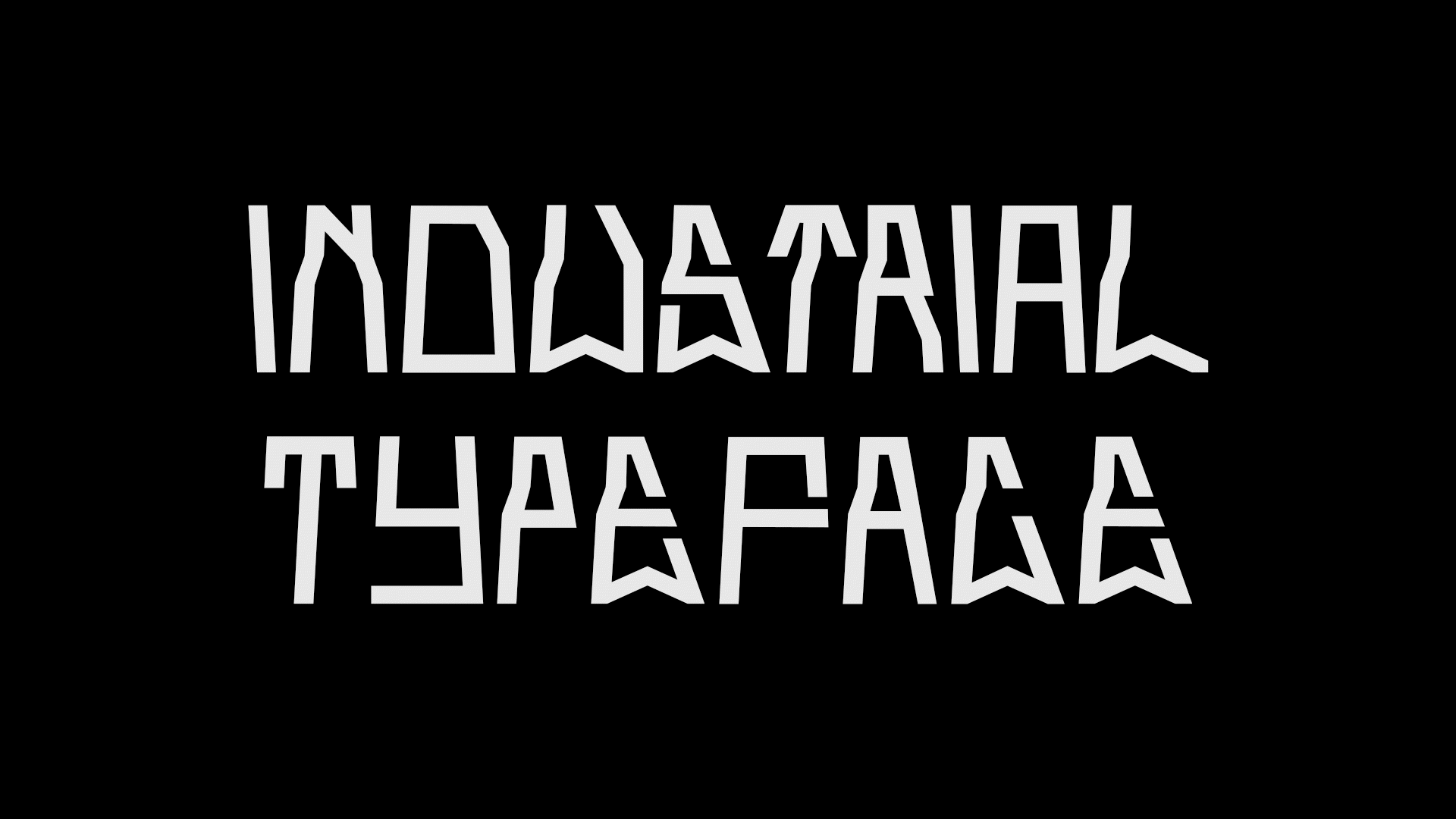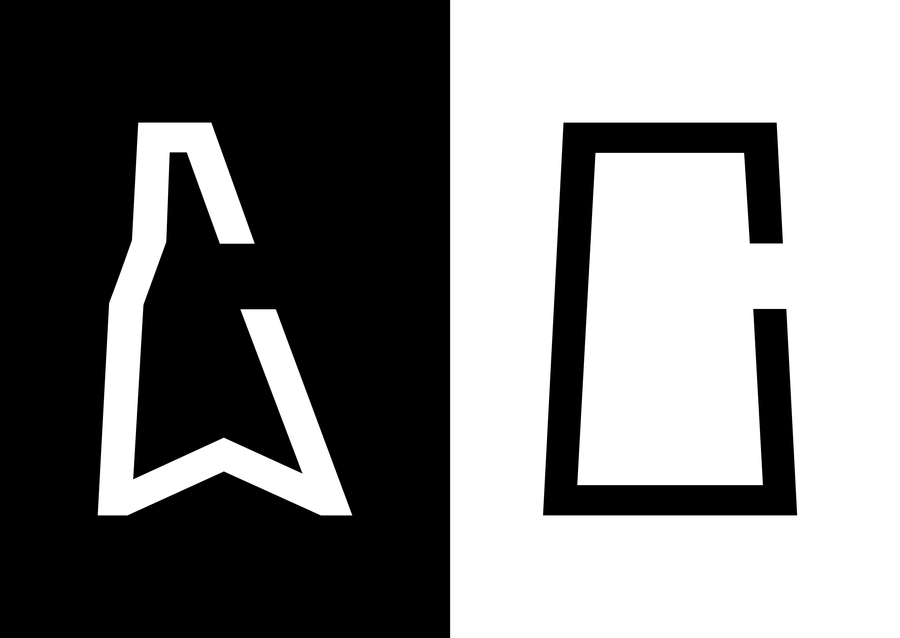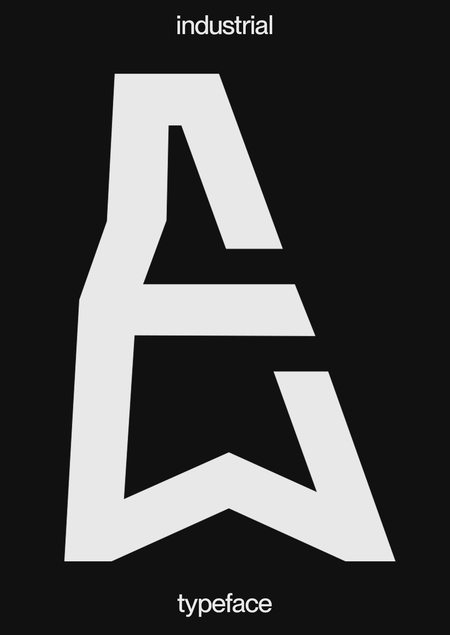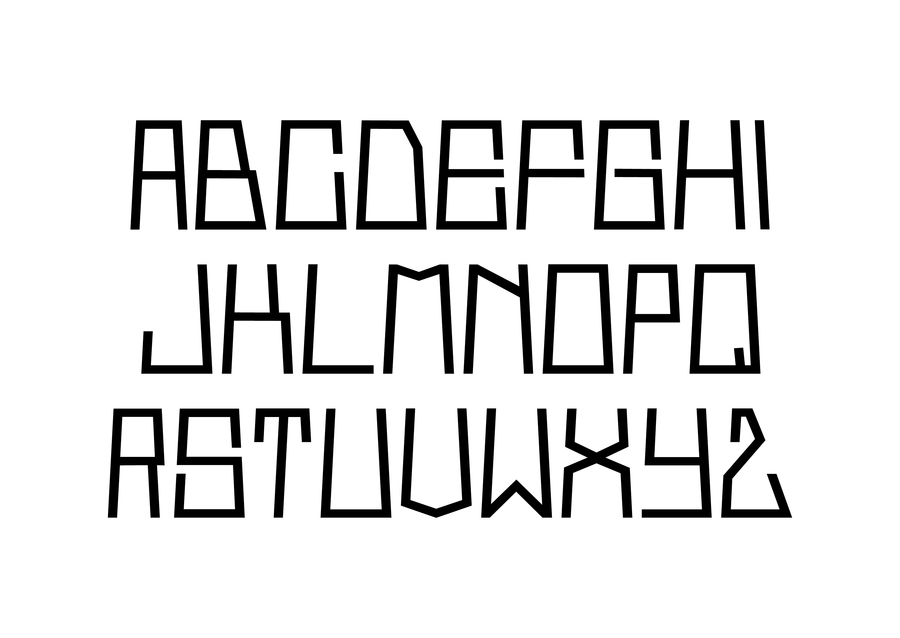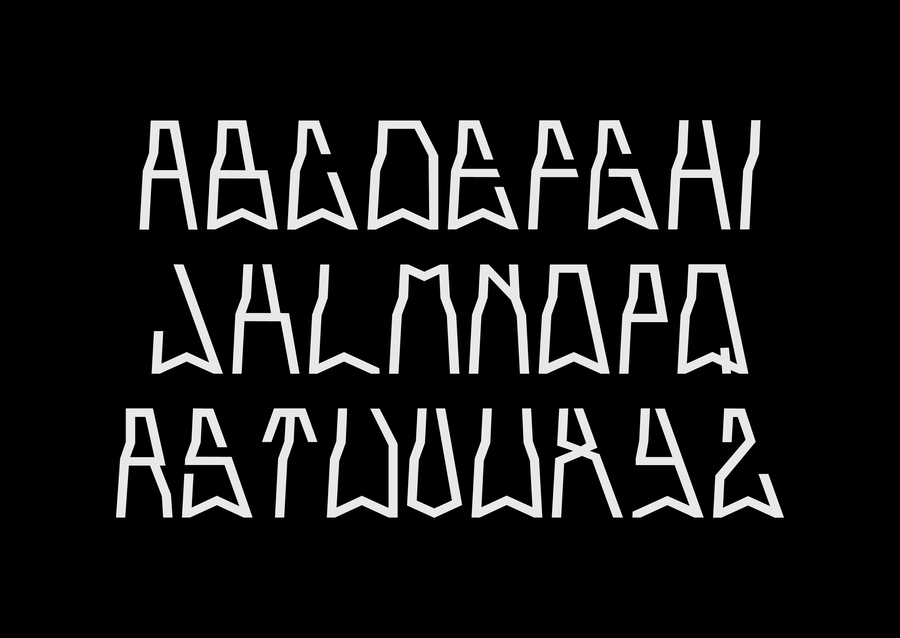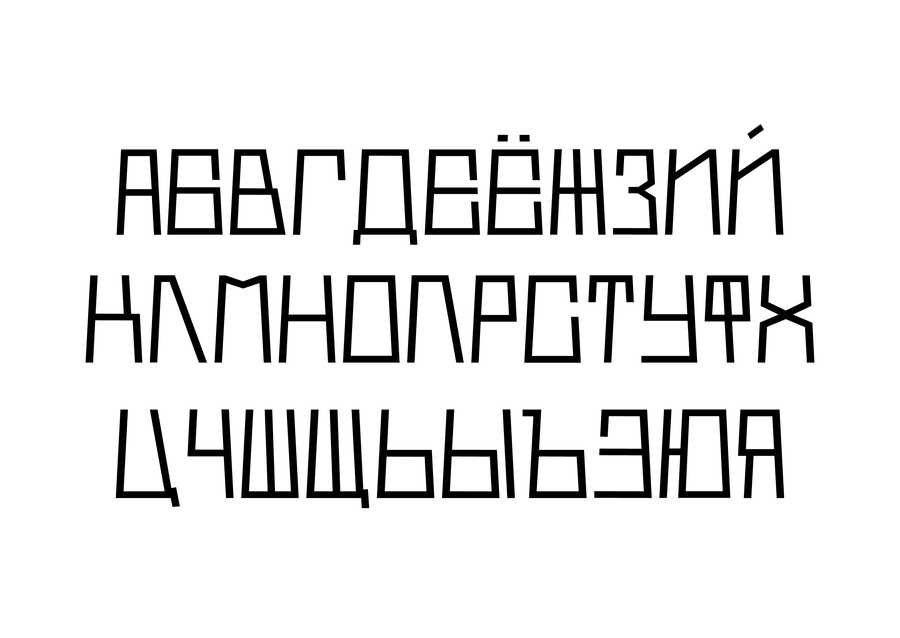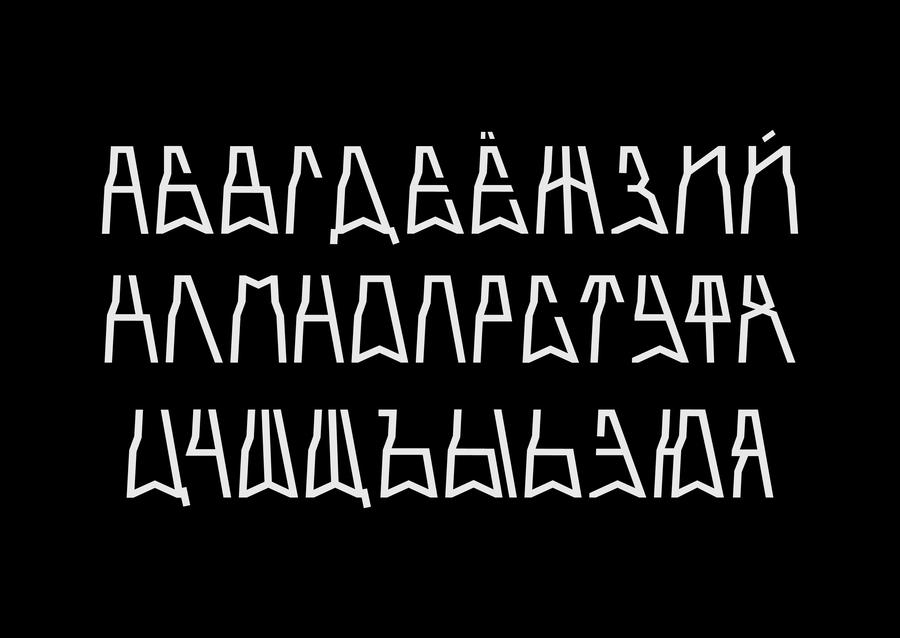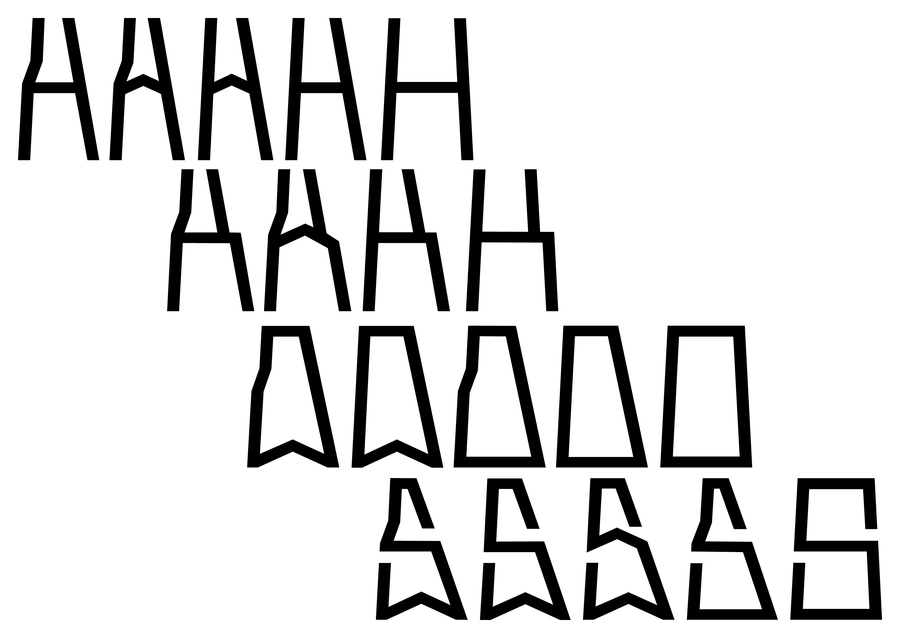
industrial font — акцидентный шрифт, вдохновленный формами опор ЛЭП. В шрифте содержится много альтернативных начертаний, что позволяет делать набор более разнообразным.
основная касса состоит из символов, построенных по единому принципу: треугольное основание, существенное сужение к верху, и фиксированные углы наклона. альтернативная же касса построена принципу упрощения, но сохранения пирамидообразной формы. между же символами из этих двух касс существует от 1 до 3 альтернатив на каждую букву.
indastrial typeface стал основой для айдентики пространства «Фабрика 1830». «Фабрика» — это арт-квартал на территории балашихинской хлопкопрядильной фабрики, основанной в 1830 году князем иваном трубецким.